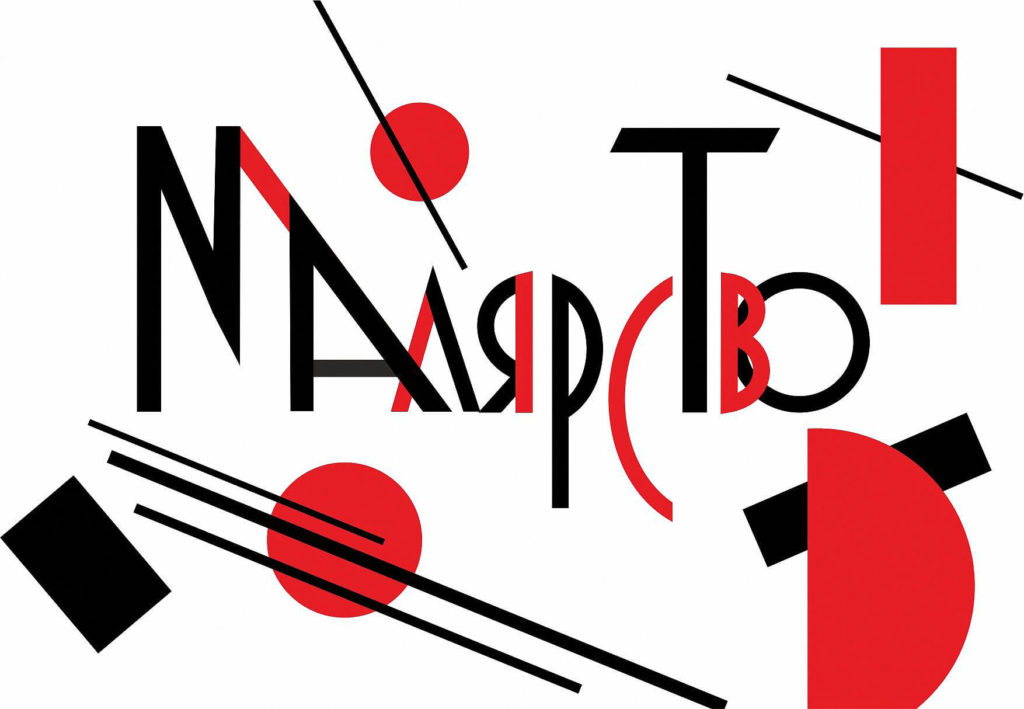
это уникальный цветной шрифт от дизайнера Алены Моргуновой (Malena), выпущенный в 2018 году. Относящийся к авангардному стилю, он сочетает геометрические формы с динамичными живописными мазками, создавая эффект ручной росписи. Шрифт поддерживает кириллицу и латиницу, а также включает альтернативные глифы для большей выразительности. Это отличный выбор для заголовков, постеров и креативных проектов, где требуется яркость и индивидуальность. Скачать бесплатно можно на нашем сайте